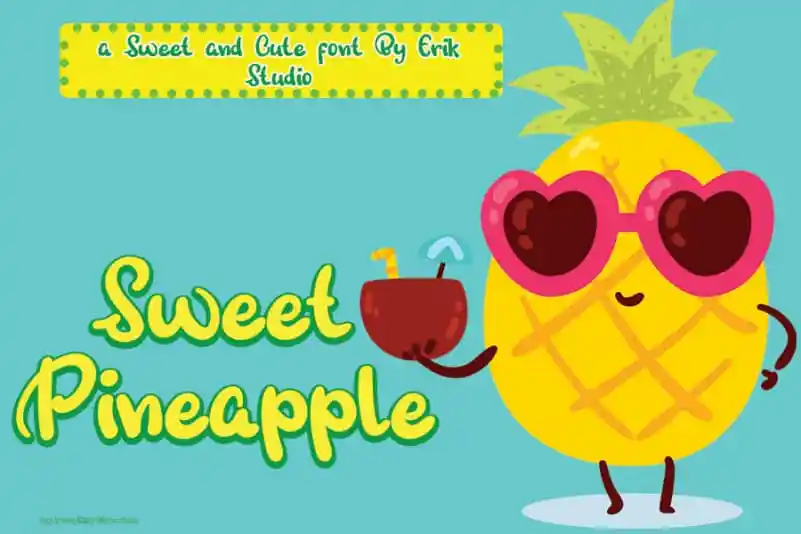
Sweet Pineapple Display Font – Download Grátis
A Sweet Pineapple Display Font é uma fonte tipo-cálice romântica que cria um toque delicado e alegre para qualquer projeto. Com seus caracteres dançando ao longo do baseline, esta fonte é perfeita para criar cartões de aniversário ou convites nupciais, projetos que exijam uma personalização romântica e encantadora. A Sweet Pineapple Display Font traz à vida sua essência alegre com um toque delicado, ideal tanto em design gráfico quanto em produção editorial. Seja para cartas de amor ou apenas para aqueles momentos especiais que merecem mais atenção, esta fonte é uma escolha perfeita para adicionar um toque especial e encantador ao seu projeto. Não importa o projeto, a Sweet Pineapple Display Font é uma excelente opção para criar memórias ainda mais memoráveis com textos elegantes e divertidos.